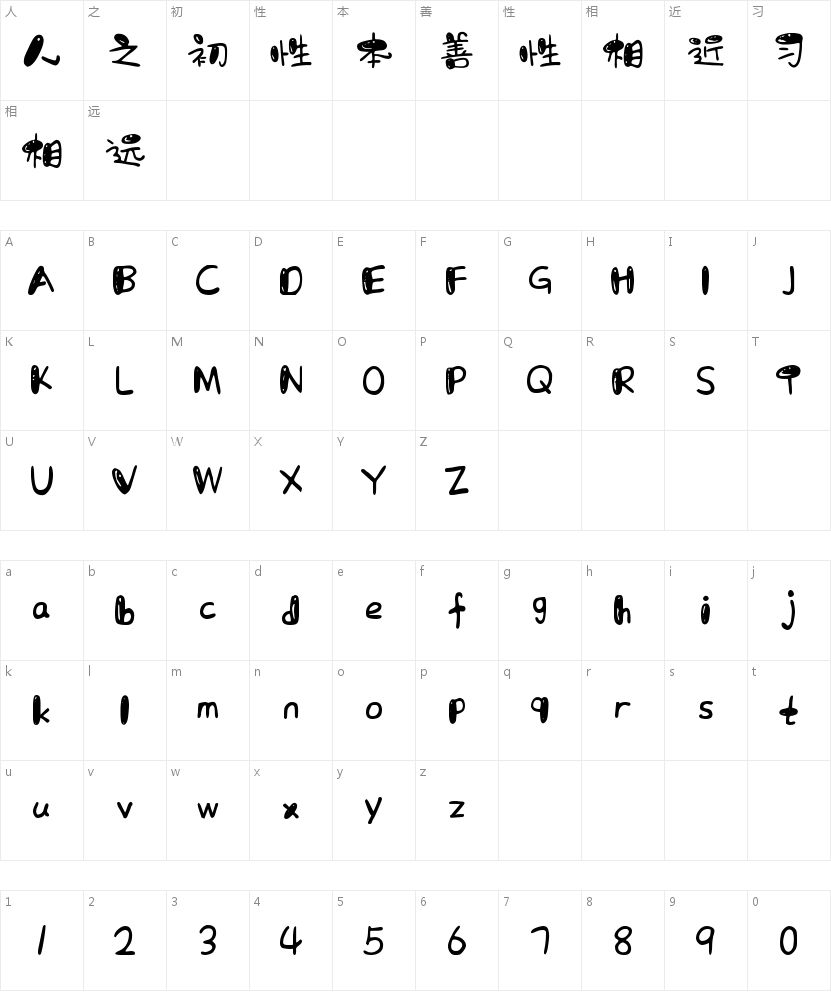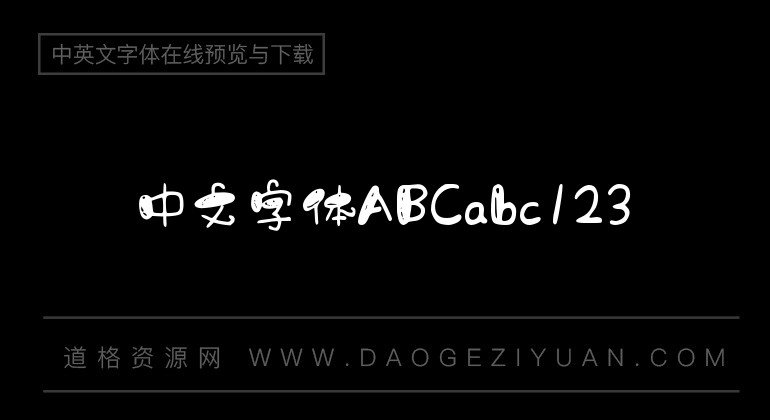
Aa白云苍狗野马尘埃
"Aa白云苍狗野马尘埃"是一款比较特别的字体,其名称可以直译为"白云苍狗野马尘埃"。它的设计理念是结合了传统书法与现代设计元素,形成了一种独特的艺术风格。 此字体的特点是线条流畅,笔画变化多样,蕴含了一定的动感和张力。其笔画的粗细和大小也非常有特色,给人一种非常个性化和独特的感觉。此外,它的整体风格非常的现代化,并且非常适合一些具有动感和时尚感的设计。 总体来说,Aa白云苍狗野马尘埃是一款非常别致的字体,其独特的设计风格可以为你的设计作品增添一份独特的艺术韵味。
Aa白云苍狗野马尘埃是一款非常不错的手写艺术字体,具有很好的视觉感,适合于文化类的宣传设计、商业类品牌的广告和产品包装设计以及个性化文字排版等较多场景。
Aa白云苍狗野马尘埃字符映射图